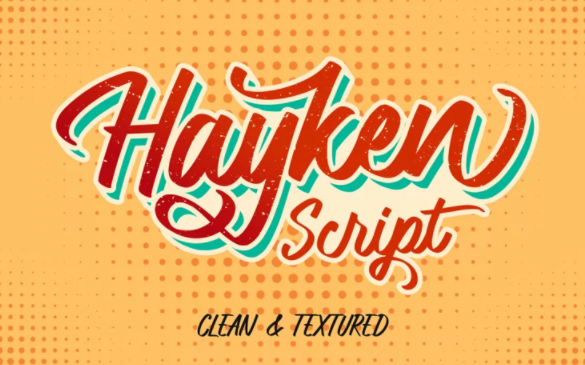
Fontbundles Hayken Script Font 2021
[Fontbundles] Hayken Script Font (2021)
Hayken Script - кистевой шрифт с динамичным и энергичным стилем. Существует два типа стилей (чистый и текстурированный). Он может использоваться для различных целей, таких как заголовки, логотипы, дизайн футболок, бланки, вывески, этикетки, информационные бюллетени, плакаты, бейджи и любой другой дизайн, которому нужен уникальный, яркий шрифт.